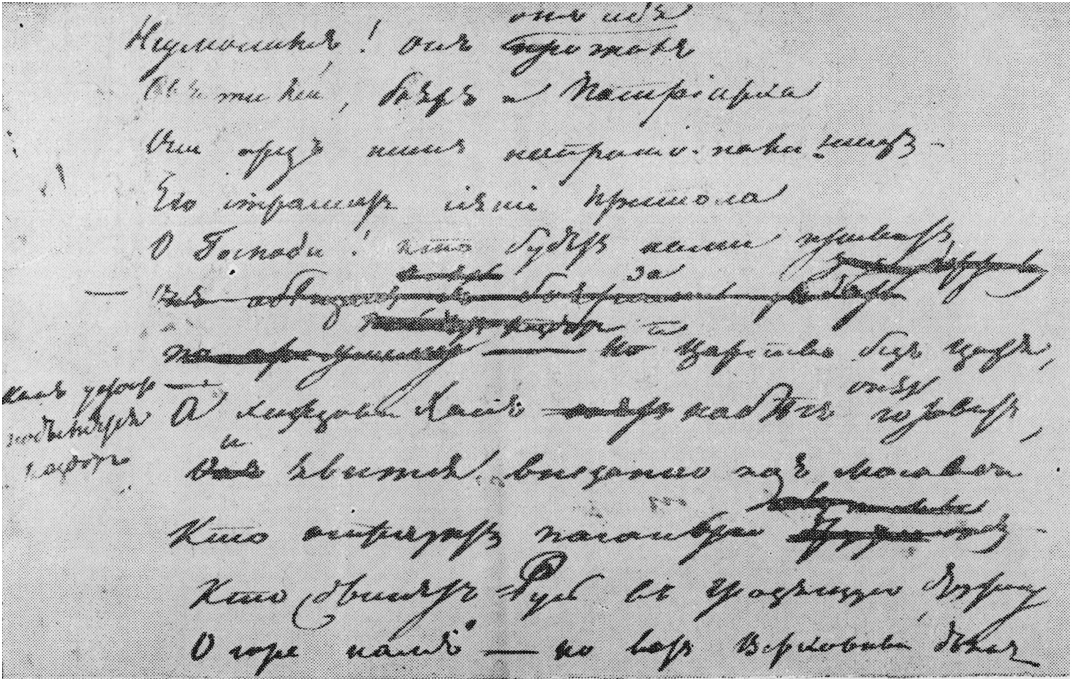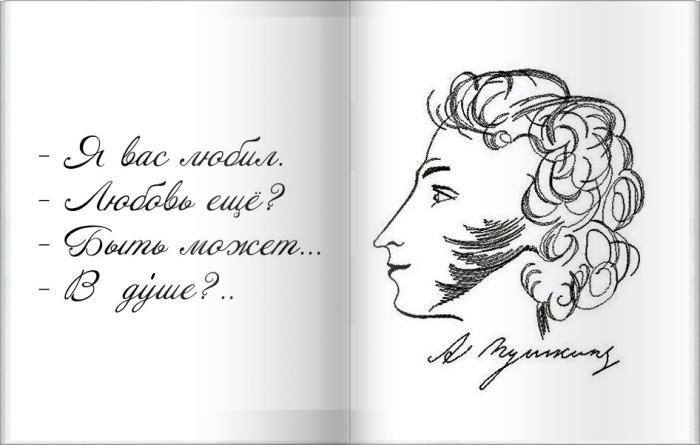
Шрифт по имени Pushkin — Год Литературы
Вряд ли 21 год назад, накануне торжеств, посвященных 200-летию великого русского поэта, широкая общественность обратила внимание на появление нового шрифта Pushkin, созданного на основе почерка Александра Сергеевича.
Популярность способствовала возникновению второй версии шрифта. Это была скорее группа шрифтов, объединенных одним названием: Pushkin… Однако обо всем по порядку.
1999 год. Ребята из Тверского КСП ВНИИСВ готовили к выпуску очередной номер клубного журнала «Слух и Голос». В год юбилея Пушкина это было музыкальное путешествие по его стихотворениям, повестям и сказкам. Журнал выходил (и выходит до сих пор) два раза в год и готовился с особенной тщательностью. Основное внимание отдавалось текстам песен, иллюстрациям и, конечно же, шрифту – в каждом номере он был новым.
Именно в этот момент у
Эмиля Якупова – главного редактора журнала и по совместительству директора шрифтовой компании «ПараТайп» – возникла идея создать шрифт на основе почерка поэта.
По задумке шрифт должен был использоваться в заголовках.
Благо к тому времени у главреда и его коллег уже сформировался технологический опыт подготовки шрифтов на основе почерка. Довольно быстро удалось найти достаточное количество автографов, и рабочий вариант был собран всего за месяц.
Первая версия распространилась настолько широко, что, казалось, шрифт используют уже в быту. Например, текст песни «Вальс-бостон», нанесенный на бутылку водки с тем же названием, совсем не соответствовал авторскому представлению о шрифте.
Но популярность все же принесла пользу: спустя несколько лет при создании «Альбома стихов Пушкина» издатели столкнулись с необходимостью иметь несколько оцифрованных вариантов почерка, отличающихся как минимум по годам. Ими планировалось набрать тексты стихотворений, для которых не сохранилось автографов.
Альбом так и не вышел, но разработку новой версии шрифта это не остановило. Еще несколько лет анализа и поисков привели к группе начертаний, разных по характеру почерка – от мелкого, но достаточно разборчивого до более размашистого, с несколькими вариациями по насыщенности.
Шрифты того времени нельзя было наполнить современными контекстуальными подстановками и стилистическими наборами знаков. Но с помощью небольшого количества альтернатив и вариантов дополнительных концевых форм всё же удалось оживить и разнообразить текст при наборе.
Возможно, что в будущем увидит свет расширенная и дополненная новыми свойствами и альтернативами версия. Но это будет уже совсем другая история.
Серия шрифтов «Пушкин» разработана для фирмы «ПараТайп» в 1999–2004 годах (дизайнер Геннадий Фридман). Шрифт создан на основе автографов А.С. Пушкина. В комплект знаков шрифта включены альтернативные варианты некоторых букв, характерные для почерка поэта. Шрифт «Пушкин Скрипт» в двух начертаниях основан на рукописях 1815 года и содержит комплект знаков для набора помимо русского на основных западноевропейских языках. «Пушкин Один» создан на основе наиболее аккуратно написанных документов.
«Пушкин Два» имитирует вариант мелкого, но тем не менее достаточно разборчивого почерка. «Пушкин Три» также имеет два начертания разных насыщенностей и имитирует автографы, отличающиеся размашистым написанием букв. Шрифты серии «Пушкин 1, 2, 3» содержат только буквы русского алфавита. В дополнение к ним спроектирован шрифт «Пушкин Франс» в западноевропейской комплектации.
Русский гражданский шрифт. 1708–1958 101
Мы рассмотрели в общих чертах развитие рисунков типографских
шрифтов в России в первой половине XIX века. Это время, когда выхо¬
дили первые издания произведений гениев русской литературы —
А. С. Пушкина, М. 10. Лермонтова, Н. В. Гоголя.
В каких типографиях и какими шрифтами набирались эти издания?
Произведения А. С. Пушкина, вышедшие в начале 20-х годов
в типографии Августа Семена в Москве, набирались шрифтами типа
Дидо, отражавшими по рисунку еще стиль классицизма1. Многие сочи¬
нения Пушкина, вышедшие в Петербурге в 30-х годах в типографии
Департамента народного просвещения, набирались шрифтами слово¬
литни Плюшара раннего периода2.
Шрифты эти еще мало отличались
от московских ооразцов Августа Семена. Первое собрание сочинений
А. С. Пушкина, которое начало выходить в 1838 году, было набрано
шрифтом кегля 12 типографии Экспедиции заготовления государствен¬
ных бумаг3.
Большинство произведений Н. В. Гоголя, выпущенных в 30-х и